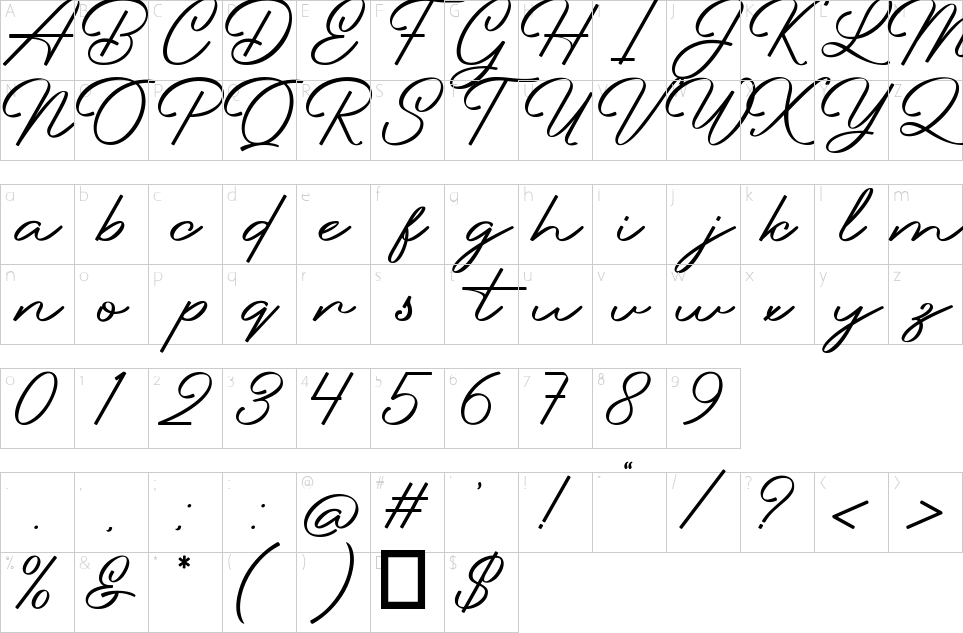
Descubra uma fonte única e moderna para seus projetos digitais com a ‘Waiting Awakmu Font’. Esta elegante fonte foi criada por RGB Studio e já foi baixada por mais de 3.864 pessoas. Com suas linhas fluidas e acentos sofisticados, ela é perfeita para adicionar um toque de elegância a qualquer projeto de design. Seja para assinaturas de e-mail personalizadas, banners de loja virtual ou qualquer outro projeto visual, esta font pode fornecer o acabamento ideal. Baixe a ‘Waiting Awakmu Font’ para Windows e Mac e reinvente a aparência de seus projetos digitais.